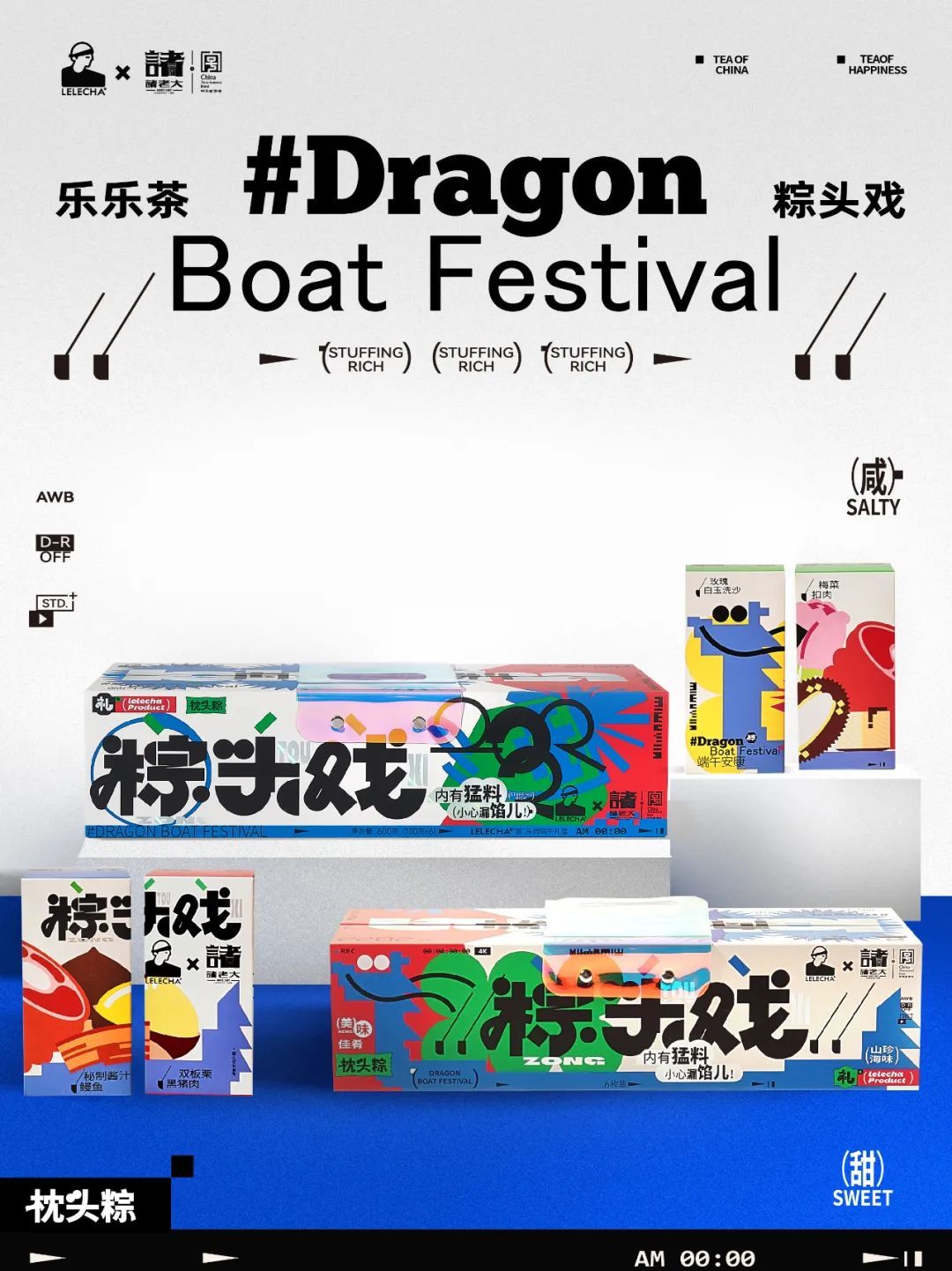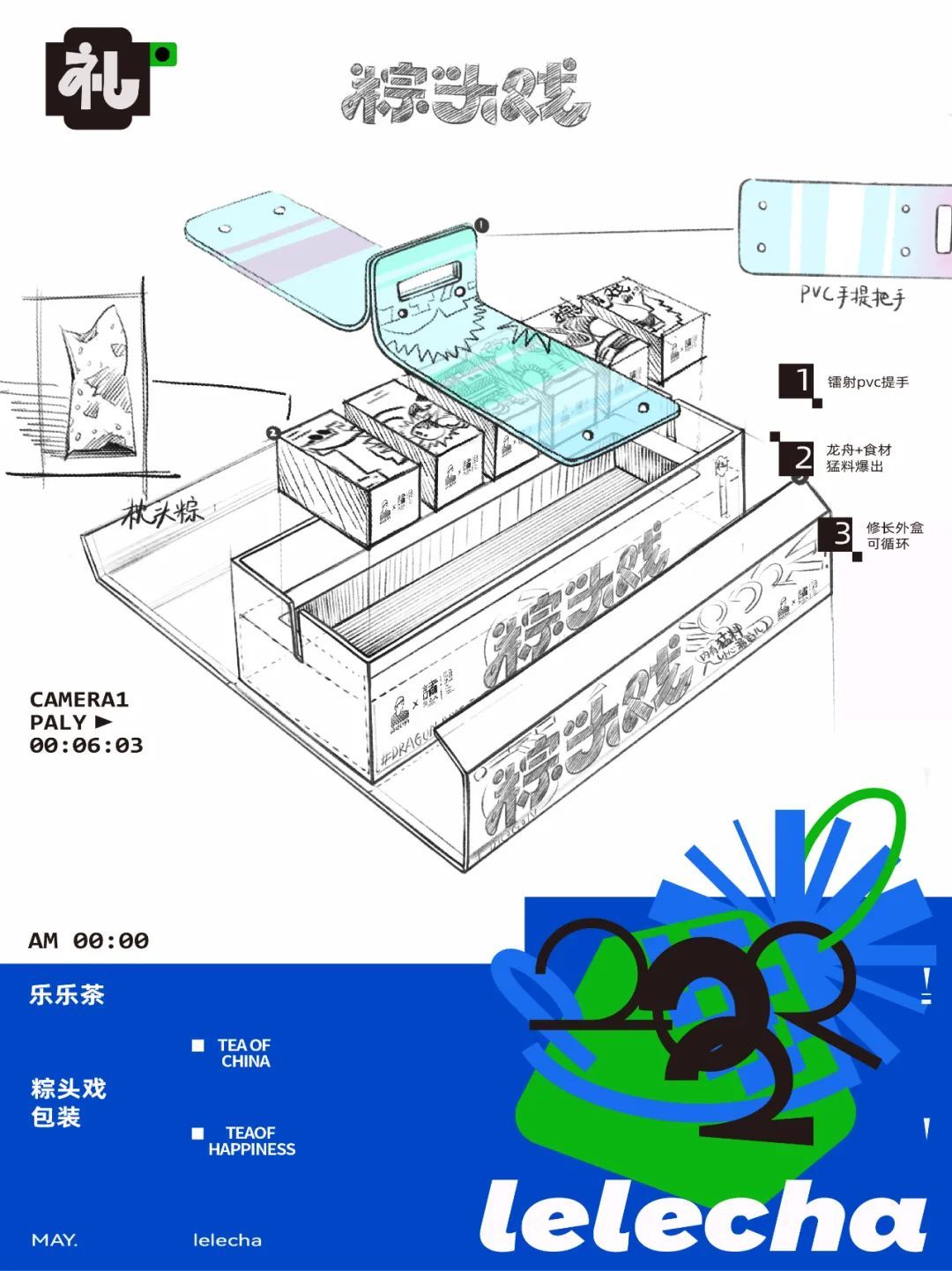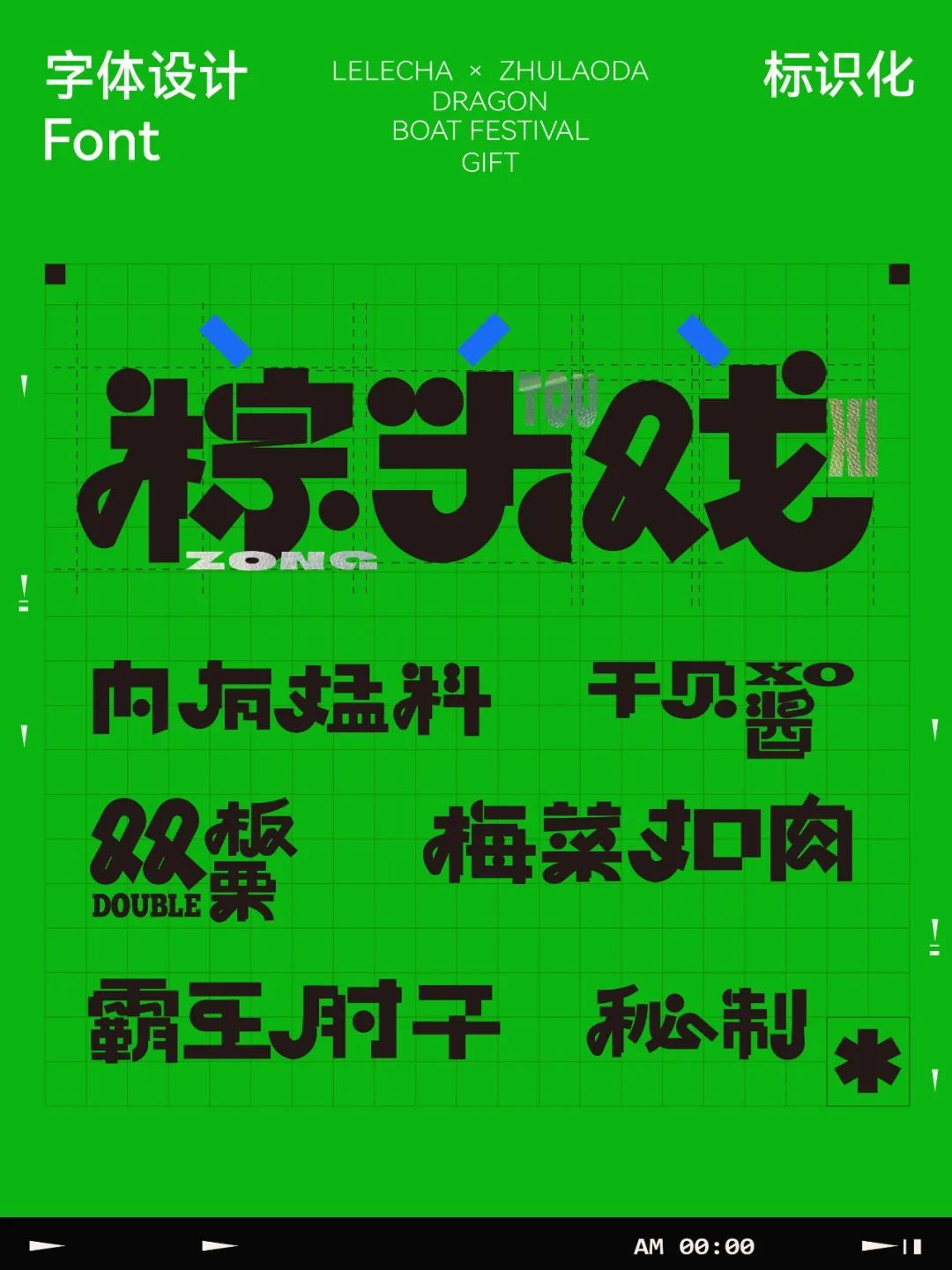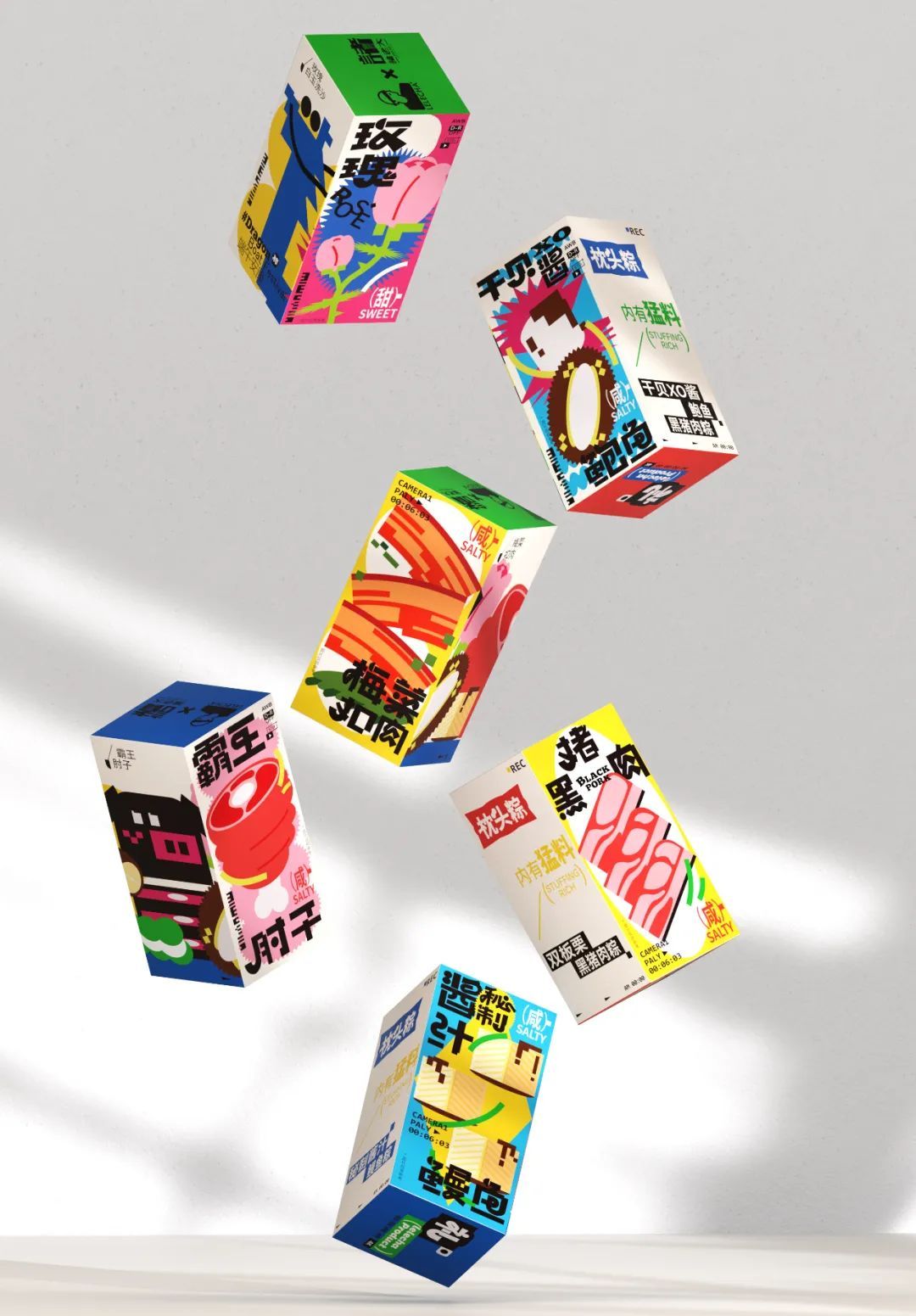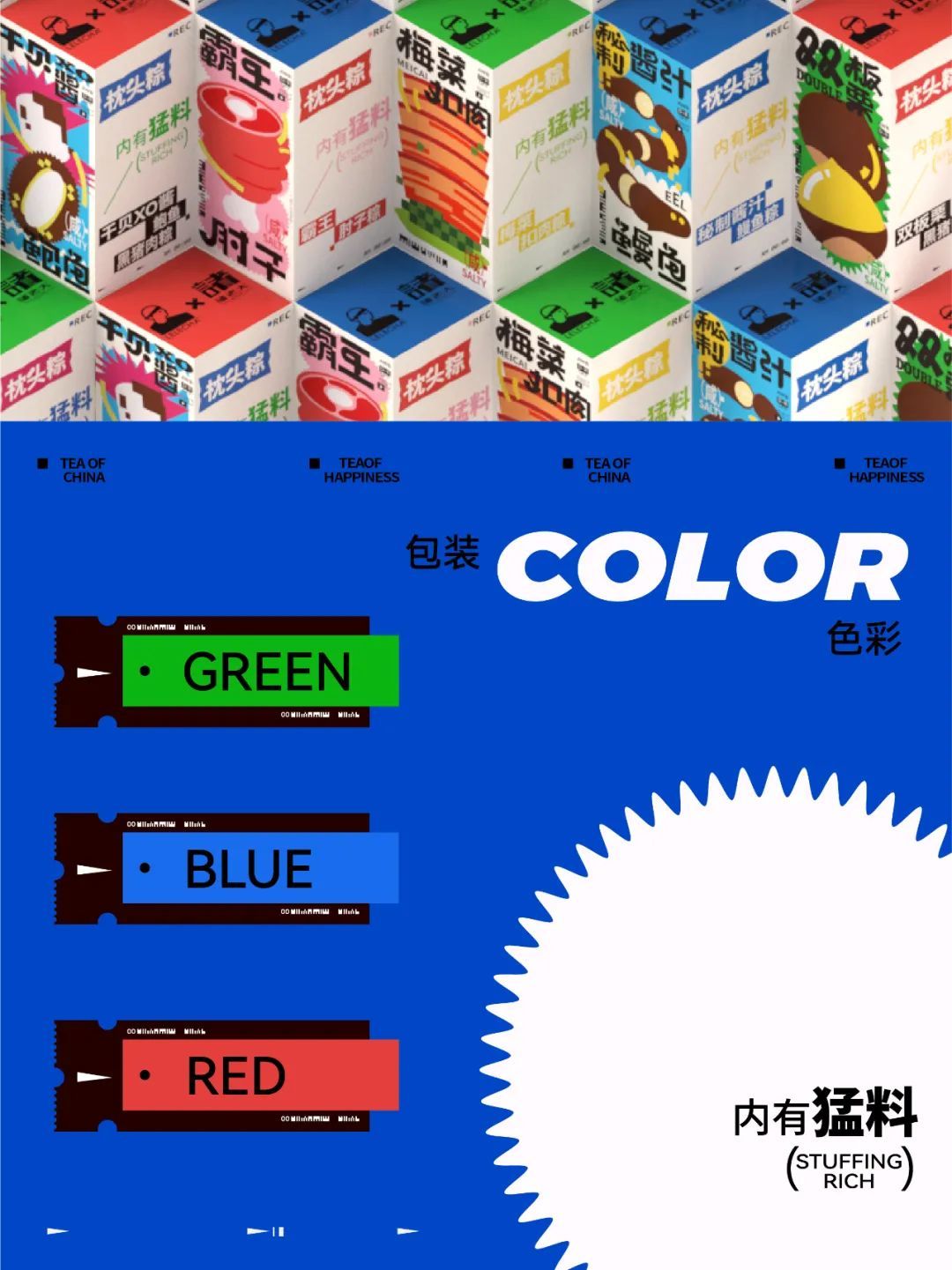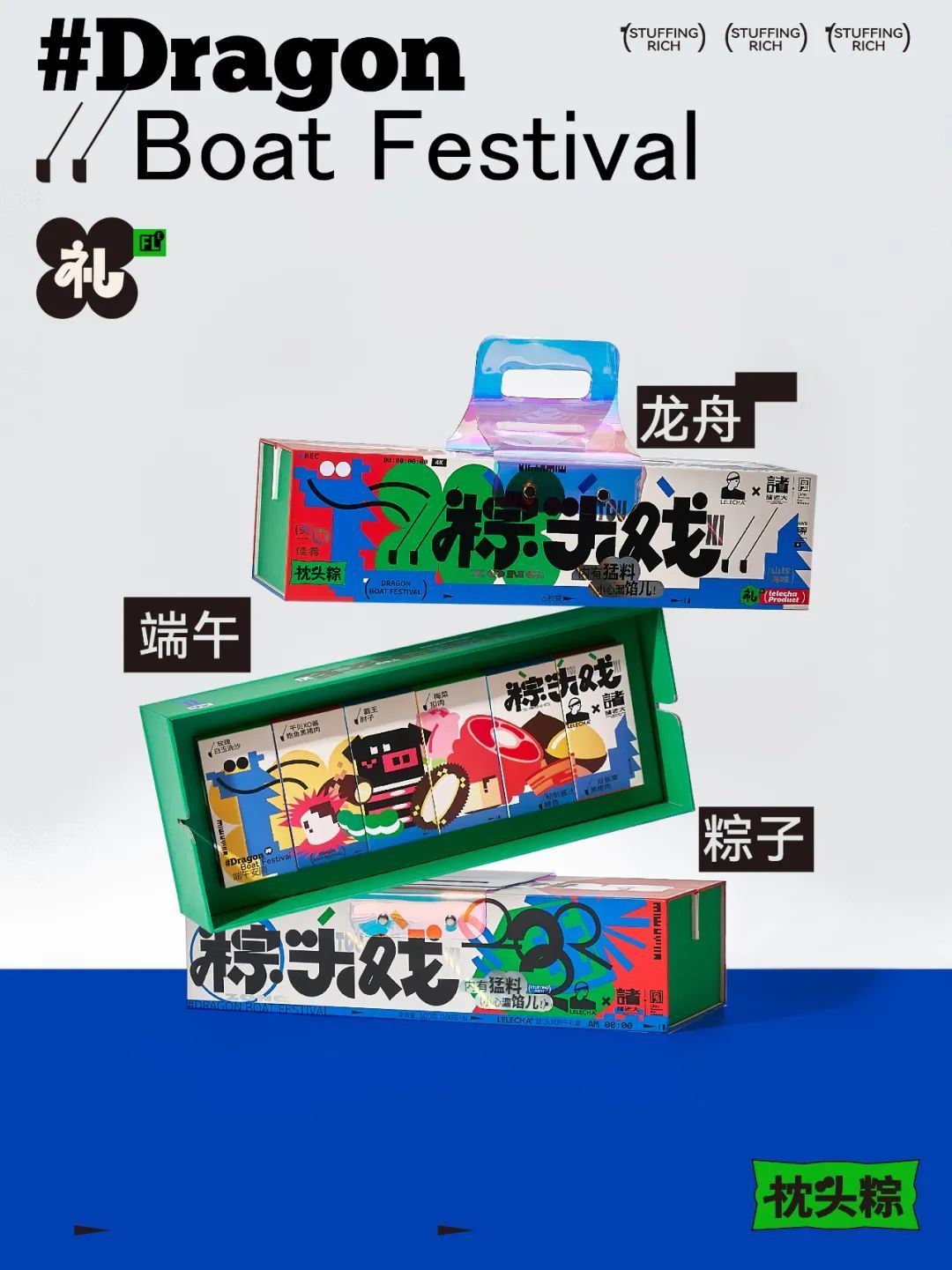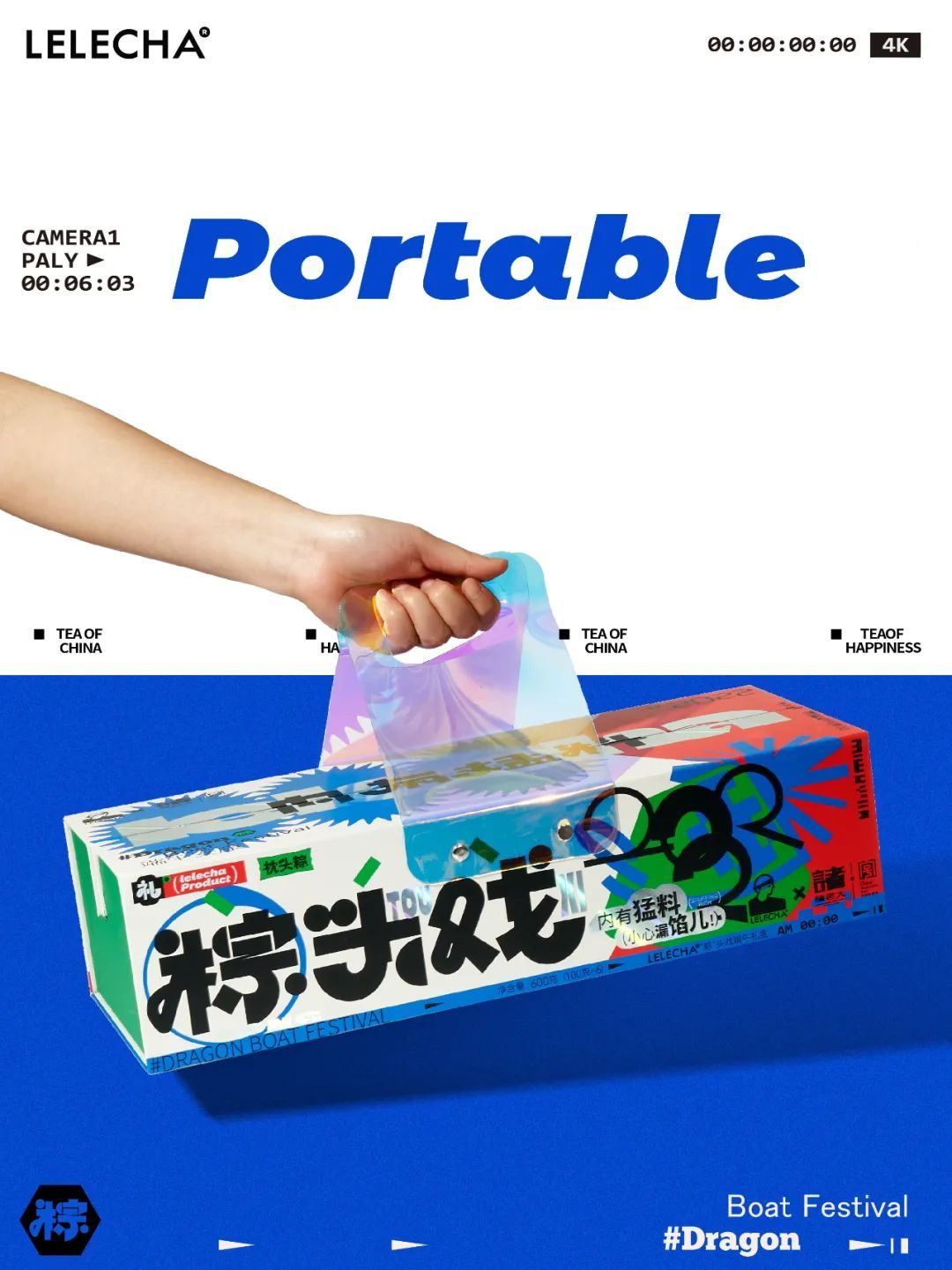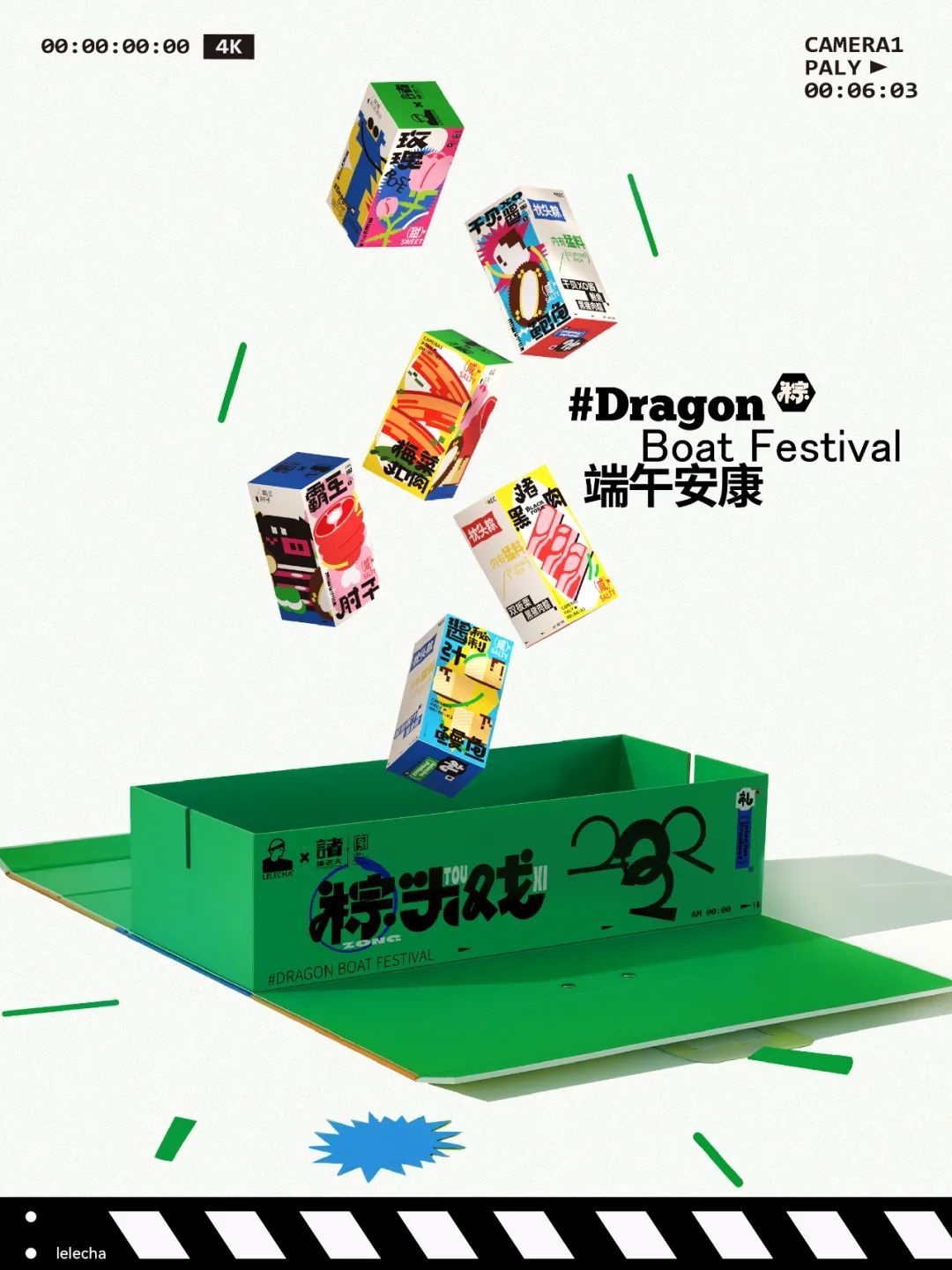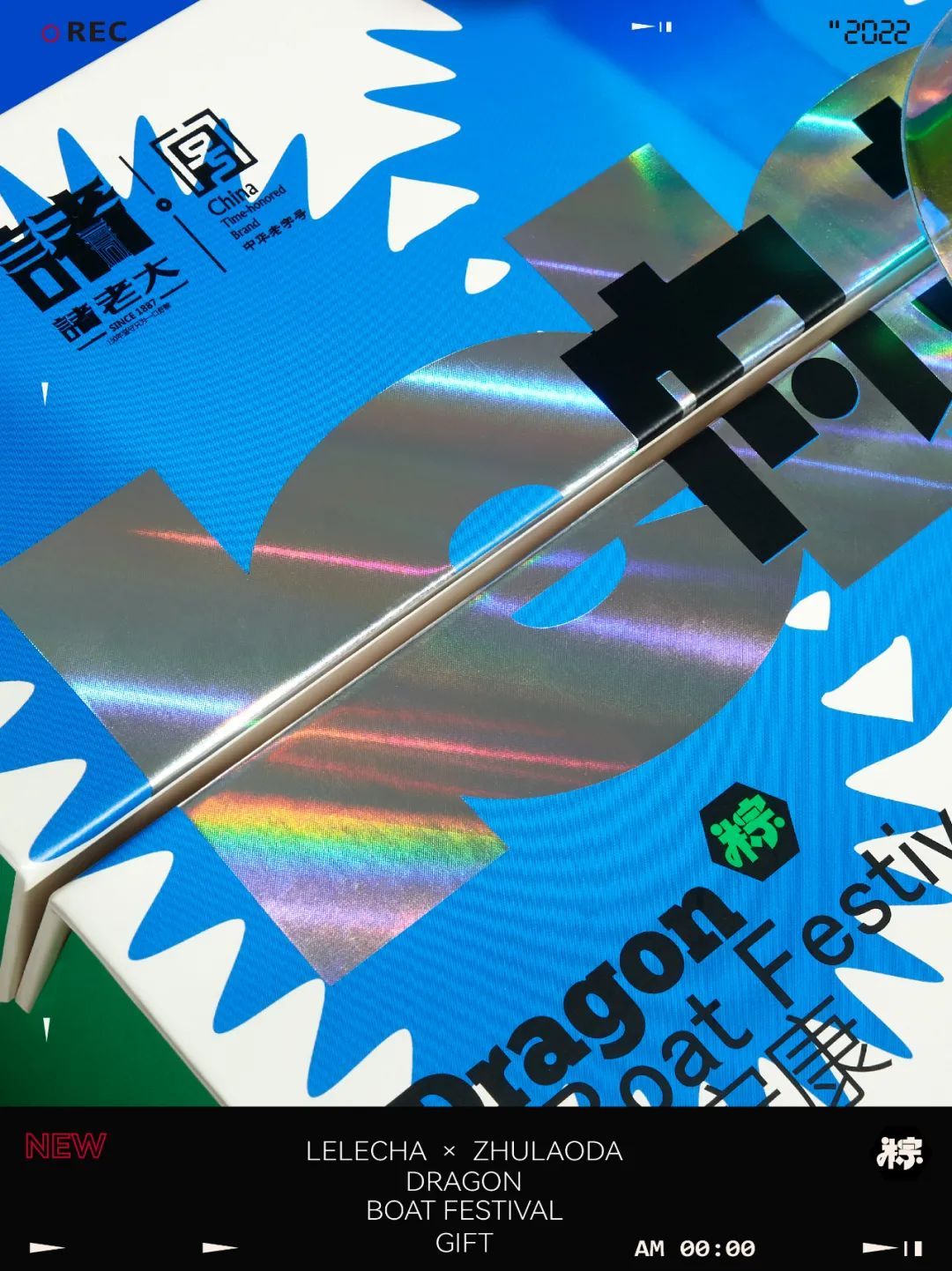
乐乐茶端午节全新包装设计
日本包装设计大师笹田史仁曾说:购物的客人在经过货架前,让商品映入眼帘的时间只有0.2秒。想要让顾客在这个瞬间惊叹一声并且愿意驻足停留,那就必须靠抢眼的包装。
随着消费者对生活品质的追求越来越高,各大品牌对于包装设计也在不断的升华,潮流性和趣味性包装在诸多产品包装中脱颖而出。
今年的端午将至,又是各大品牌包装设计争奇斗艳的时刻。在当下,一款极具美感的设计,越来越成为各品牌让自家产品出圈的重要方式。
在茶饮界更是如此,我们注意到:乐乐茶发挥一贯大胆的设计手法,针对端午推出了别出新意的“粽头戏”粽子礼盒。
“粽头戏”主题包装礼盒
乐乐茶是成立于2016年,以茶饮+软包相结合的新中式茶饮品牌。凭借着独特的设计和吸引人的产品风格风靡全国。坚持打造属于自己的品牌理念和视觉体现,成为强化消费者对乐乐茶品牌记忆的关键。
➊ 传统的,也很潮
端午节作为三大传统节日之一,主流品牌一般按照惯性思维把礼盒设计“古朴、经典”的样子。
传统的东西就不能潮?
这次,乐乐茶显然打破了界限与定律,旨在探索潮流性、无隔阂、包容的生活态度,并以传递快乐的方式通过视觉设计创造出一种持续更新的乐观情绪,这种对传统节日的破局和结构,正是乐乐茶的能量所在。
其包装设计和包装材质,让消费者无不为其着迷,设计彰显着先锋流行与艺术文化。通过新颖的视野和新潮的设计感让年轻人更爱传统节日。
“粽头戏”主题包装礼盒草图
乐乐茶端午节主视觉
➋ “粽头戏”设计解析
字体设计:
“粽头戏”包装上大篇幅运用了独特、夸张化的字体,同时又在组合中保证文字的饱满呈现,让视觉上更加活泼年轻、新潮魅力。
将字体笔画几何化,星形、方正小图形点缀装饰营造了整体氛围,增加与产品相关的趣味性设计,既能够快速缩短与消费者沟通的距离,又能够进一步彰显品牌的文化。
粽子的单独小盒,可以发现每款口味都搭配了全新的字体设计,让整个包装具有整体性的同时也能秀出口味的个性。包装盒上大量采用黑色字体,让画面更具设计感,增加了视觉分量。
颜色搭配:
通过结合非遗“枕头粽”产品和“粽头戏”的创意主题,礼盒设计保留了符合节日氛围的绿色,辅助补色红色和邻近色蓝色作为视觉延伸,形成包装的多重记忆点。大胆舍弃了厚重古朴的复古色彩,转而设定为明亮、饱和度高,对比度强烈的亮色调性。视觉上多重颜色互相碰撞,提升礼盒的品牌识别度,传达乐乐茶快乐的节日氛围。
标识图形:
包装中提取“礼”字做了灯笼状、梅花状几何化呈现,暗藏传统文化的内涵。
另外,外包装图形一面提取“龙舟”——具有节日代表性的元素进行展示,另一面则是用抽象的画面来展示“粽子爆有料”的画面,让消费者强化此款礼盒“粽子超有料”的一大特点。
内包装将粽子里面的重要食材图形抽象化处理,对相同食材采用不同的方式展现,在保持风格统一性的同时丰富了视觉的多元化。其内盒可以拼接组成整幅的龙舟载着山珍海味的画面,增加礼盒包装的互动性和趣味性。
整体从视觉上直接传递产品特点,让消费者从观感上直接感受到粽子口味的丰富和粽子内馅食材的饱满。
包装工艺:
采用镭射的工艺以及镭射pvc的提手也是一大亮点。镭射pvc提手的大胆使用,让包装增加了透气性,画面更加灵动。镭射提手反射的多彩光晕折射在包装上,将自然光与包装活泼色块天然融合,视觉观感更加丰富。
把软质内盒和硬质的外盒,通过结构的穿插组合成型,颇有趣味。用完的盒子还可以作为收纳盒循环使用。
包装特点:
“食欲感、满足感、传统节日感”围绕这三点,在保证品牌产品信息传递的同时,将礼盒画面处理的十分饱满,给人满足的感受和食欲感。
将“内有猛料”的字体放在顶部的开口处增加开盒的仪式感,打开后是内盒整幅的热闹画面,扑面而来的惊喜感。这可以在第一时间抓住消费者的目光。
❸ 总结
得年轻人得天下!新锐设计本质上就代表了年轻这一代的审美,潮流消费在国内茶饮市场已逐渐形成气候。乐乐茶打破了消费者对茶饮品牌刻板印象,打造自身品牌形象力的同时,增强潮流氛围感,吸引年轻新客流,不断探索和满足年轻用户对潮流文化以及美好生活的需求。